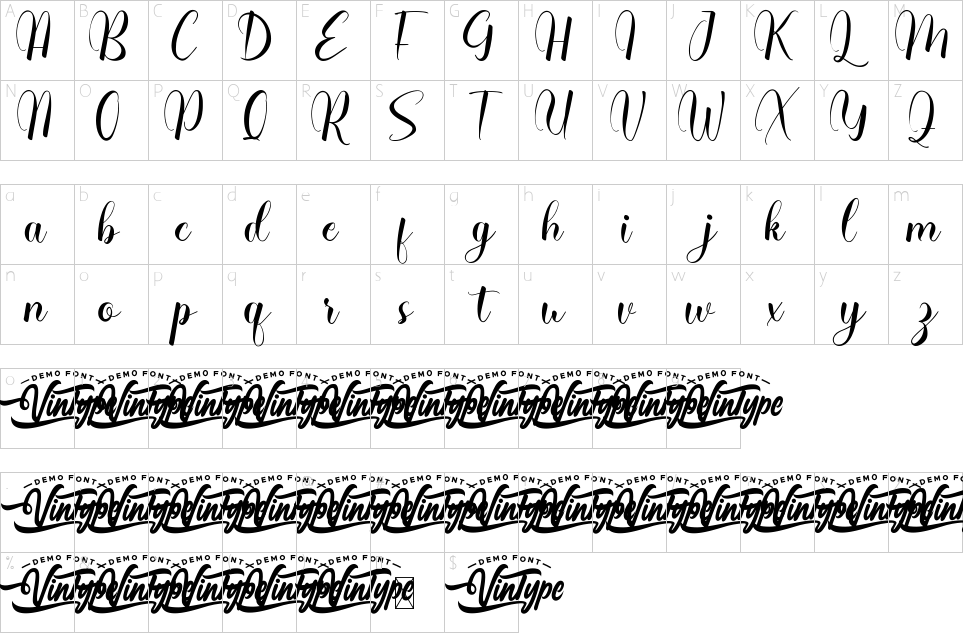
Descubra a Sabrina Month, uma fonte elegante e moderna que se destaca em qualquer projeto. Inspirada no estilo dos anos 90, a Sabrina Month oferece um toque de nostalgia ao mesmo tempo sofisticado, tornando-a perfeita para layouts digitais e projetos de design gráfico. Com uma interface confortável e facilidade de uso, essa fonte é uma escolha excelente tanto para designers iniciantes quanto para profissionais experientes. Seja para criar banners, títulos de slides, ou até mesmo para personalizar textos em suas próprias páginas web, a Sabrina Month é uma fonte versátil e de alta qualidade. Se você está procurando por uma fonte clássica que não perde o toque moderno, a Sabrina Month é uma ótima escolha. Descubra agora e adicione um toque único ao seu próximo projeto.